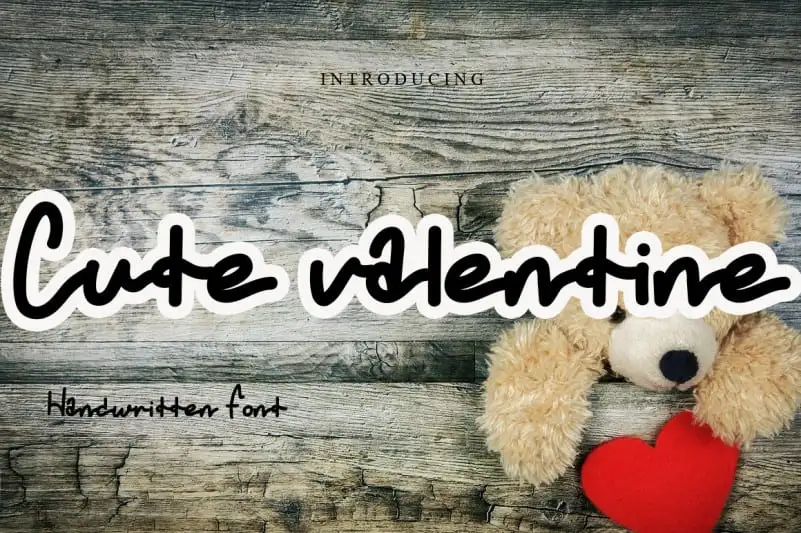
Cute Valentine Handwritten Font – Download Grátis
A fonte ‘Cute Valentine Handwritten Font’ traz uma atmosfera envolvente e natural para qualquer projeto que você desejasse dar um toque delicado e amoroso. Seu estilo único, não simétrico e intrigante é perfeito para adicionar aquele toque especial em designs de datas especiais ou projetos personalizados. Este tipo de escrita feita à mão atesta a sua capacidade única de enriquecer qualquer projeto sem deixar espaço para dúvidas sobre seu uso. Aproveite a oportunidade de dar um toque romântico e único aos seus materiais gráficos com ‘Cute Valentine Handwritten Font’, criado pelo designer levincreative. Esse é o tipo que você vai querer ter sempre à mão, garantindo que todas as suas criações estejam em harmonia com a estação ou ocasião.